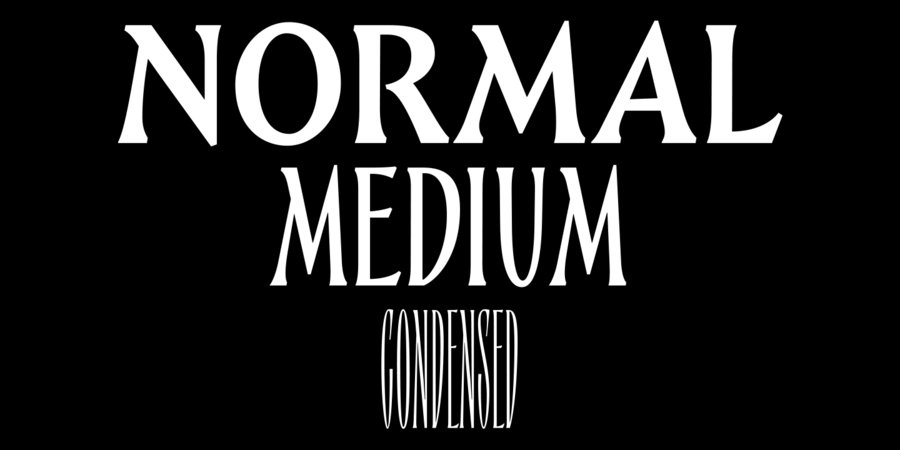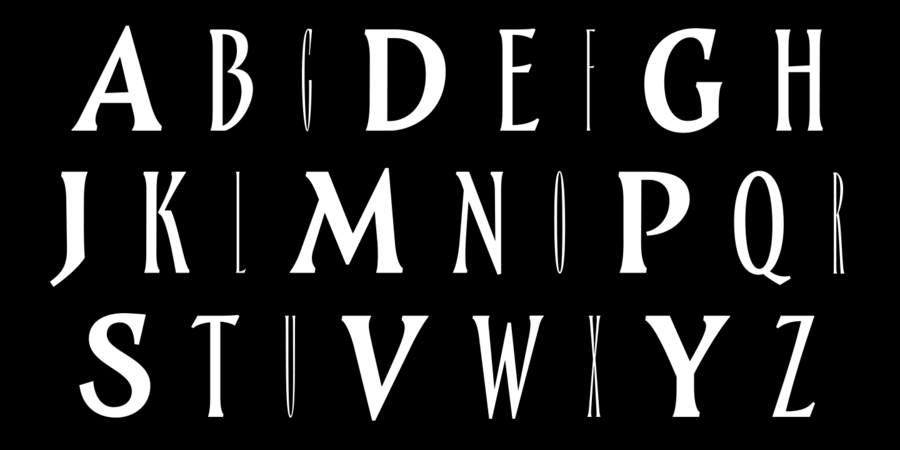
Epos (3 шрифта)
Капітальний шрифт Епос складається з трьох накреслень різної ширини й містить безліч альтернативних знаків і лігатур, підтримує латиницю та кирилицю. Переможець конкурсу Modern Cyrillic 2021. Шрифт нагадує рукописні книжкові обкладинки початку і середини 20-го століття. Шрифт розробив Денис Серебряков у 2018 році.
Асоціації з сімейством шрифтів EposОсобистість і характер гарнітури:
героїчний, благородний, класичний, красивий, виразний, характерний, пафосний, майстерний, урочистий, тріумфальний, звитяжний, епічний, дзвінкий, амбітний, легендарний, прекрасний, художній, ремісничий, римський, крафтовий, динамічний, фантастичний, племінний, імперський, старовинний, історичний, казковий, гострий, різкий, чіткий, консервативний, золотий, самобутній, оригінальний, етнічний, натуральний, традиційний, гордий, колоритний, артистичний, ювелірний, дорогий, розкішний, аристократичний, елітний, якісний, музичний, культурний, освічений, старомодний, лицарський, сміливий, королівський, пивний, кам'яний, естетичний, знаменитий, дорогоцінний, унікальний, добірний, багатий, сильний, важливий, впевнений, рішучий, кінематографічний, древній, твердий, вольний, войовничий, хоробрий, бравий, мужній, вільний, бунтівний, темпераментний, мотивуючий, активний, суворий, залізний, релігійний, добротний, біблійний, християнський, церковний, сакральний, архітектурний, високий, гучний, стрункий, тонкий, худий, стиснений, тісний
епос, література, музей, меморіал, пам'ятник, прикраса, ювелір, скульптура, надгробок, мистецтво, історія, ремесло, пригоди, живопис, фентезі, геральдика, казка, Чарівна казка, вино, замок, монета, гроші, золото, цукерки, шоколад, алкоголь, коньяк, Трофей, нагорода, театр, реконструкція, фольклор, музика, літопис, тату, татуювання, сувенір, гетьман, горілка, срібло, розкіш, етнографія, бібліотека, культура, ресторан, лицар, обладунки, сувій, гравюра, король, карти, дракон, меч, антикваріат, пиво, таверна, паб, гра, художник, архітектура, їжа, преміум, готель, коштовності, віскі, годинник, кіно, поезія, церква, храм, монастир, влада, отаман, зброя, коваль, тютюн, бій, м'ясо, банкнота, сир, легенда, комп'ютерна гра, Біблія, камінь, захід сонця, шолом, філософія, ром, люкс, свічки, релігія, ікона Гарнітура має ознаки стилів: